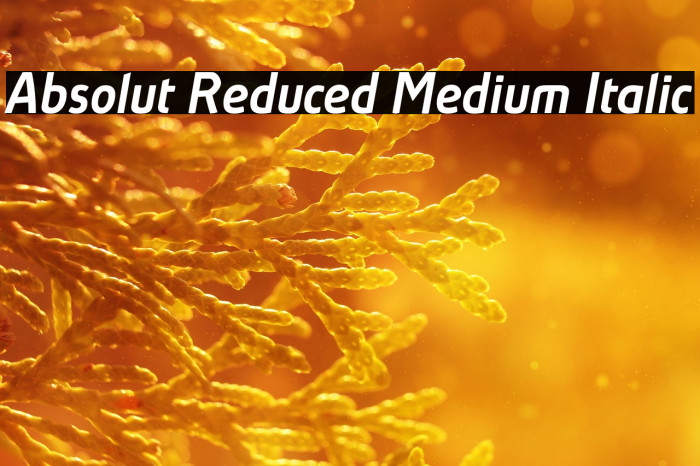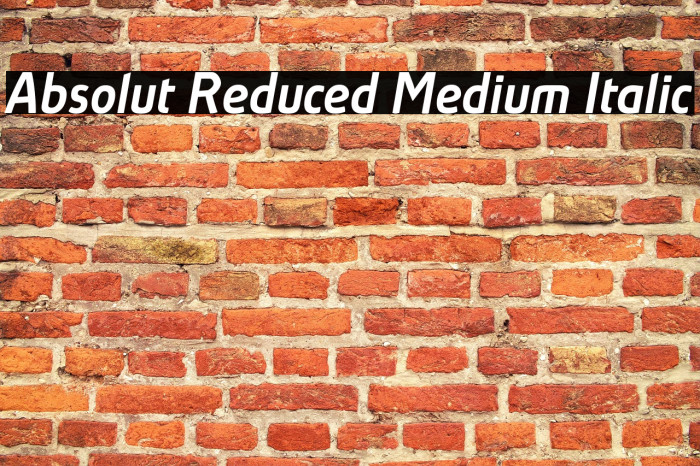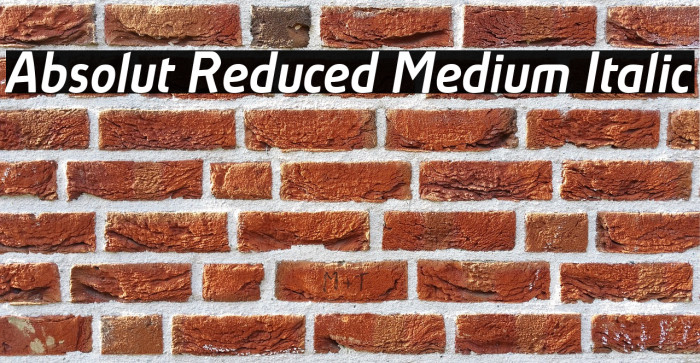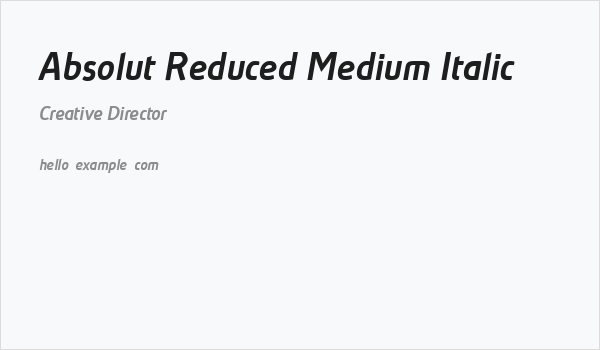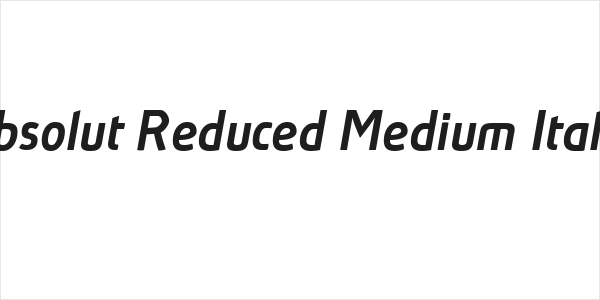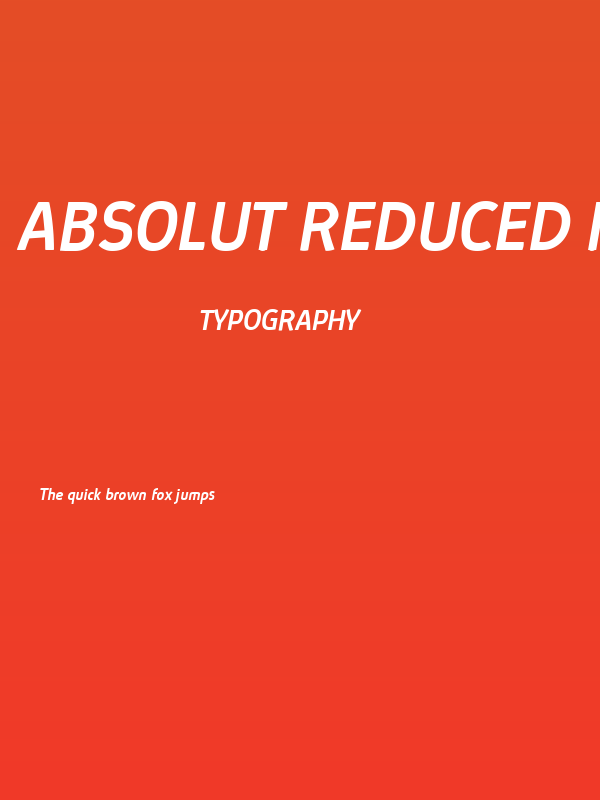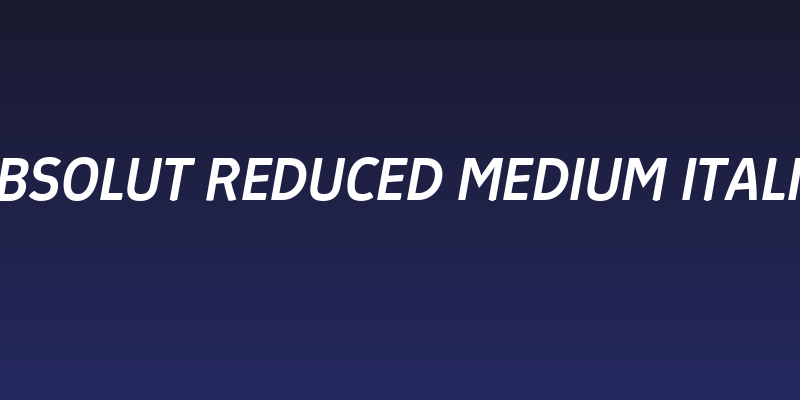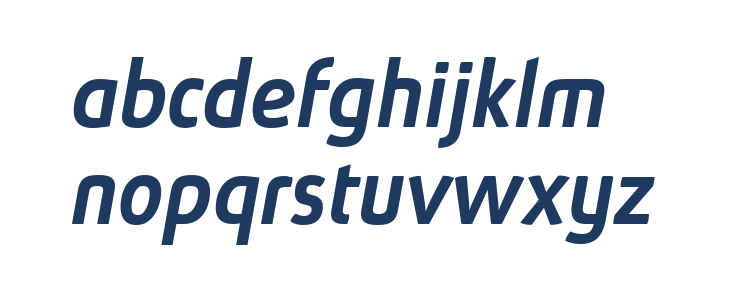
Absolut Reduced Medium Italic Font
| Progetti proposti | Ideal for branding, advertising, and editorial design projects where a contemporary and professional look is desired. |